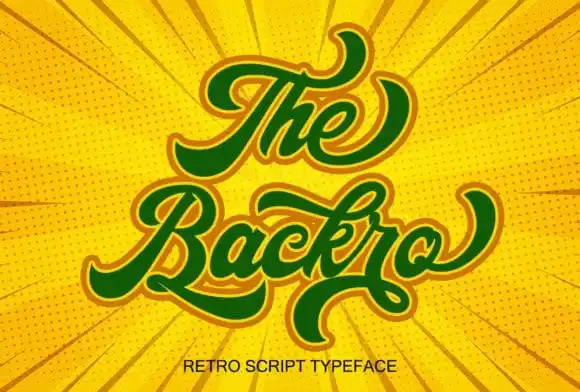
The Blacko Script Font – Fonte Grátis
The Blacko Script Font
Através do designer Sealoung na 99designs, chegamos à The Blacko Script Font, uma fonte script forte e ousada que combina elegância e versatilidade. Desenhada para criar impressionantes designs, The Blacko é curvada e arredondada, exibindo um estilo vintage único que se destaca em qualquer marca ou projeto. Seu formato fluído de escrita a mão oferece uma sensação refinada que torna-o perfeito para os projetos preferidos dos usuários. Descrito como um estilo distintivo e eterno, não hesite em explorar este design para dar vida à sua próxima criação visual, garantindo assim um toque único e singular ao seu trabalho.